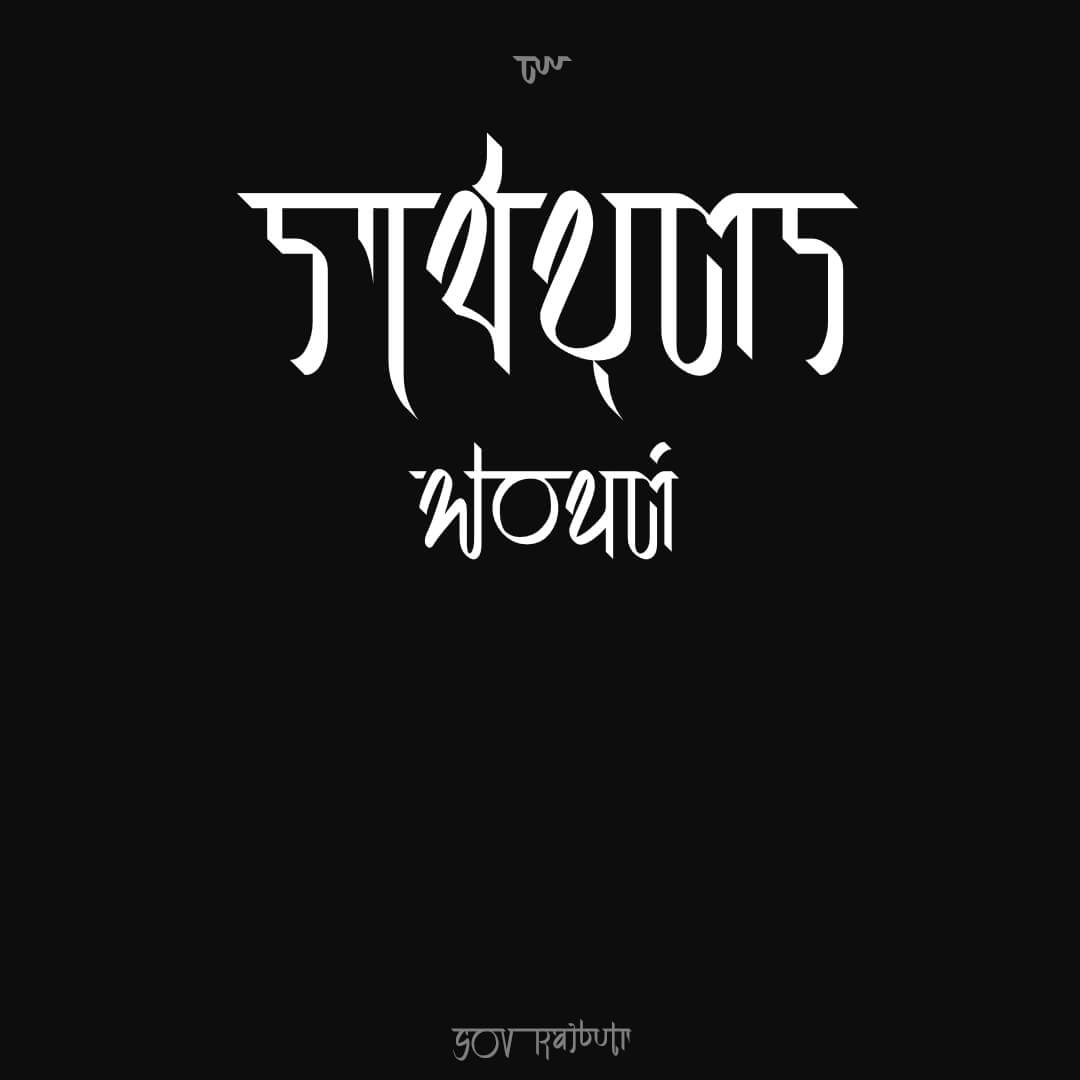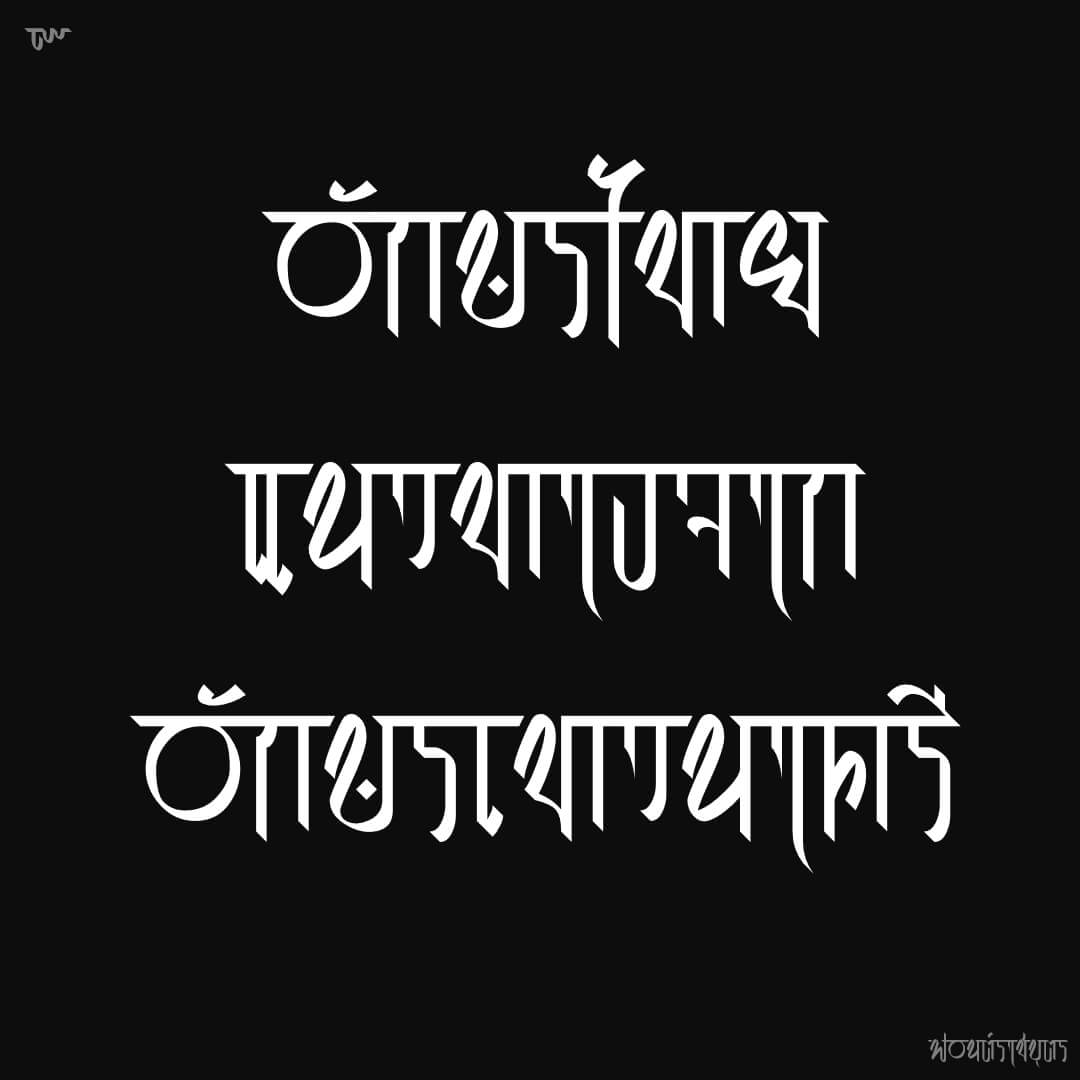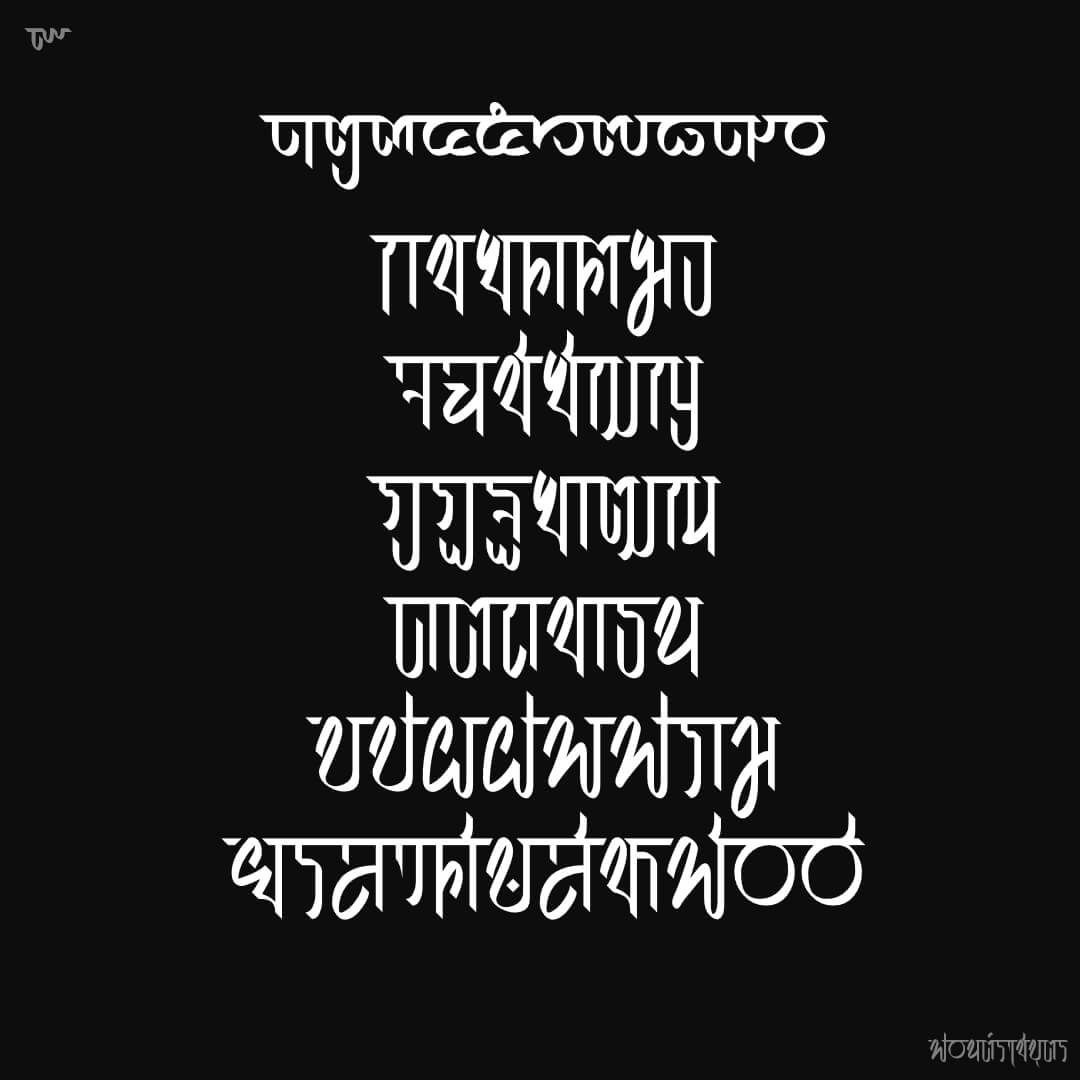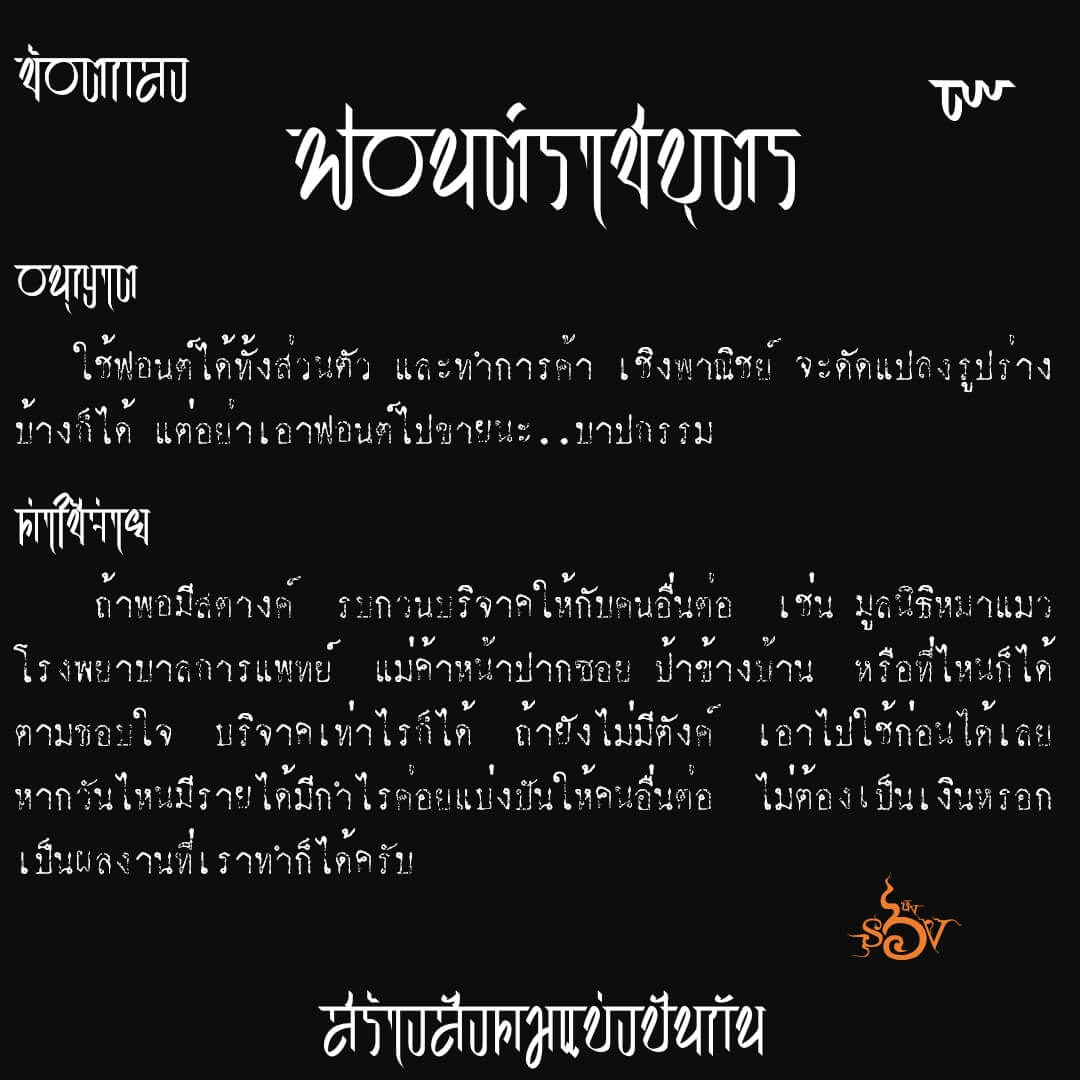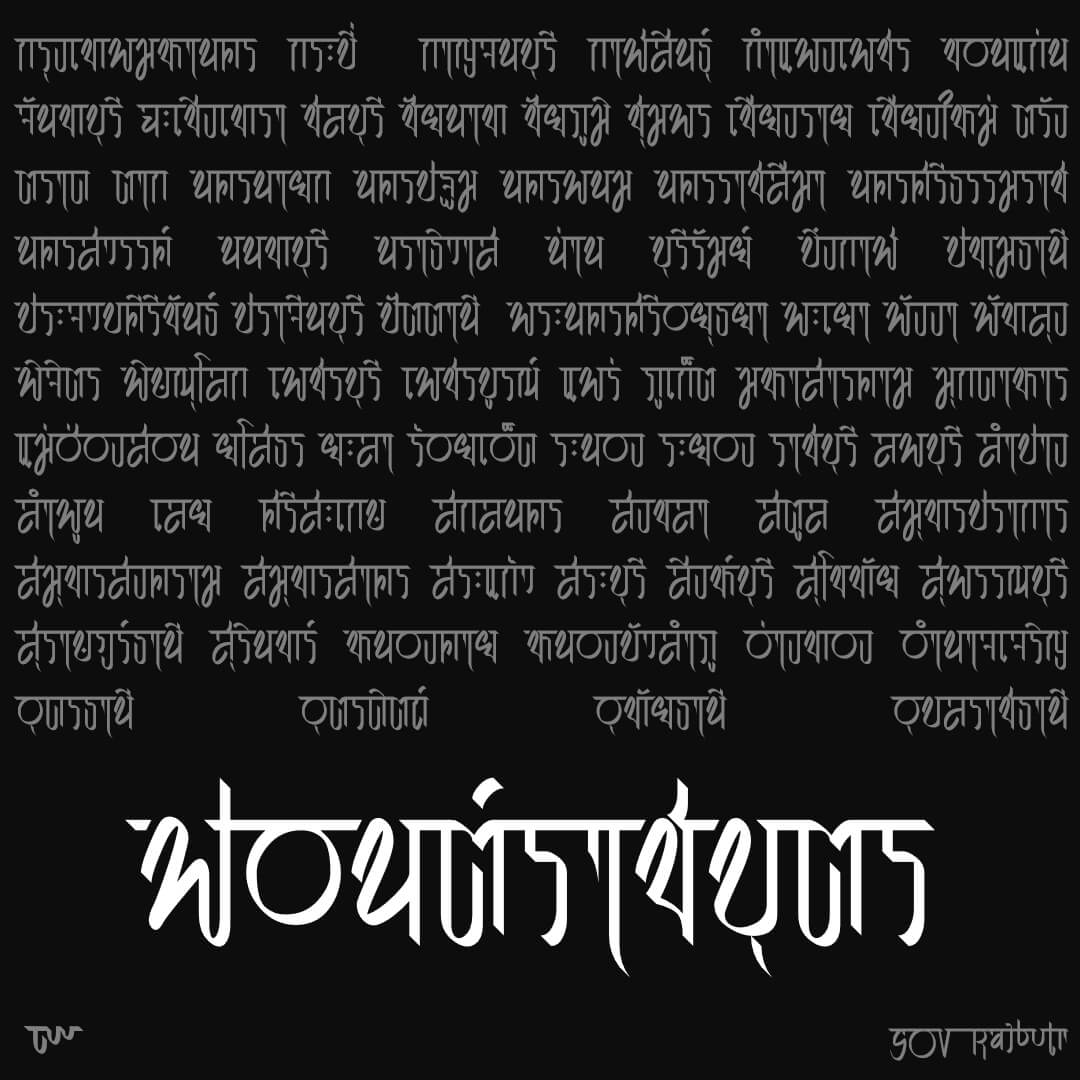
ฟอนต์ราชบุตร – ตั้งโจทย์ไว้ว่า… ฟอนต์ที่มีเส้นเชื่อมโยงกัน และใช้ปากกาหัวตัด แนวทางจึงมาจากอักษรเทวนาครี อินเดีย แถมด้วยโจทย์มุมปากกา 135 องศา… ออกแบบอักษรใหม่หมด
เบื้องหลังการออกแบบ : ฟอนต์ ราชบุตร
ราชบุตร (SOV_Rajbutr)